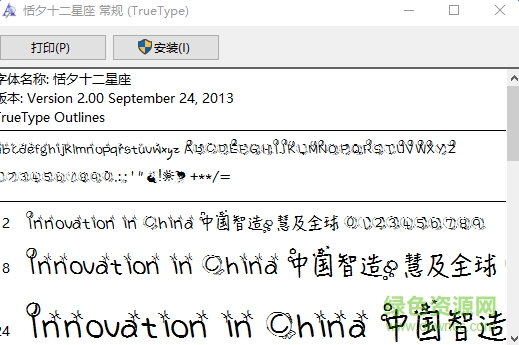
十二星座泡泡鱼字体是一款很特殊的电脑个性字体,这款字体写出来的字不像普通字体那样就是很规范的,就像这款字体的名字一样,在写出来的字体上面是会有泡泡的装饰的,是不是很可爱呢,喜欢的朋友就快来绿色资源网下载吧。
十二星座泡泡鱼字体是一款很受年轻朋友们喜欢的电脑艺术字体,因为这款字体写出来的字特别好看、有魅力,如果你也喜欢这款字体就快来绿色资源网下载吧。